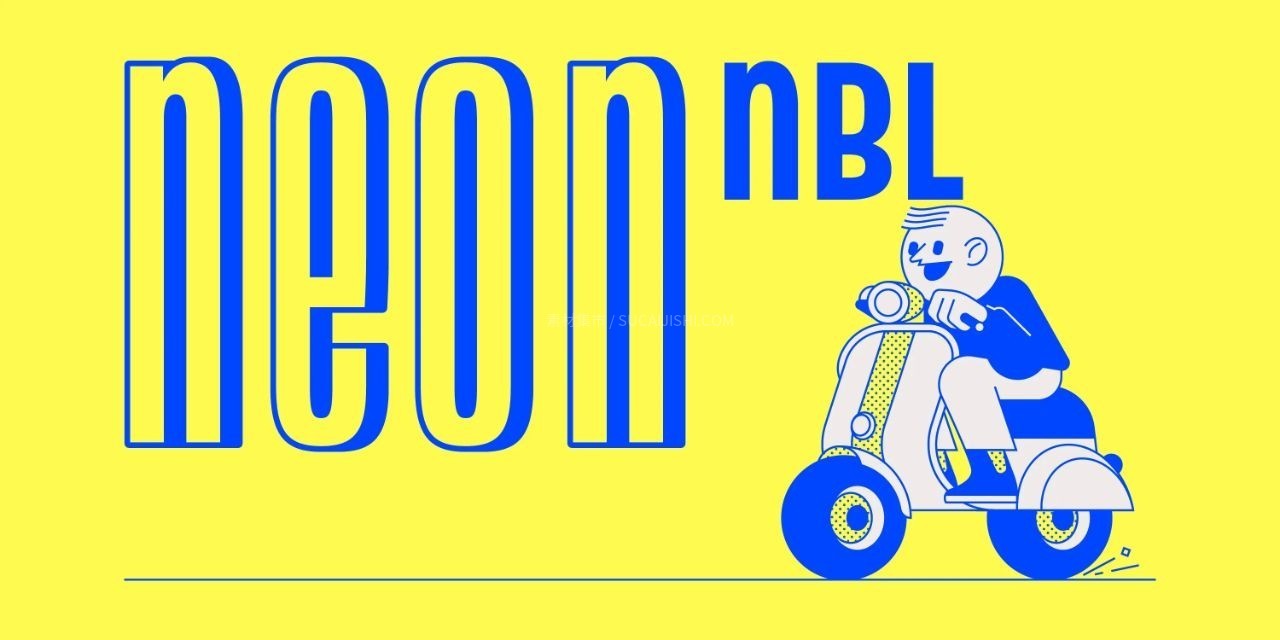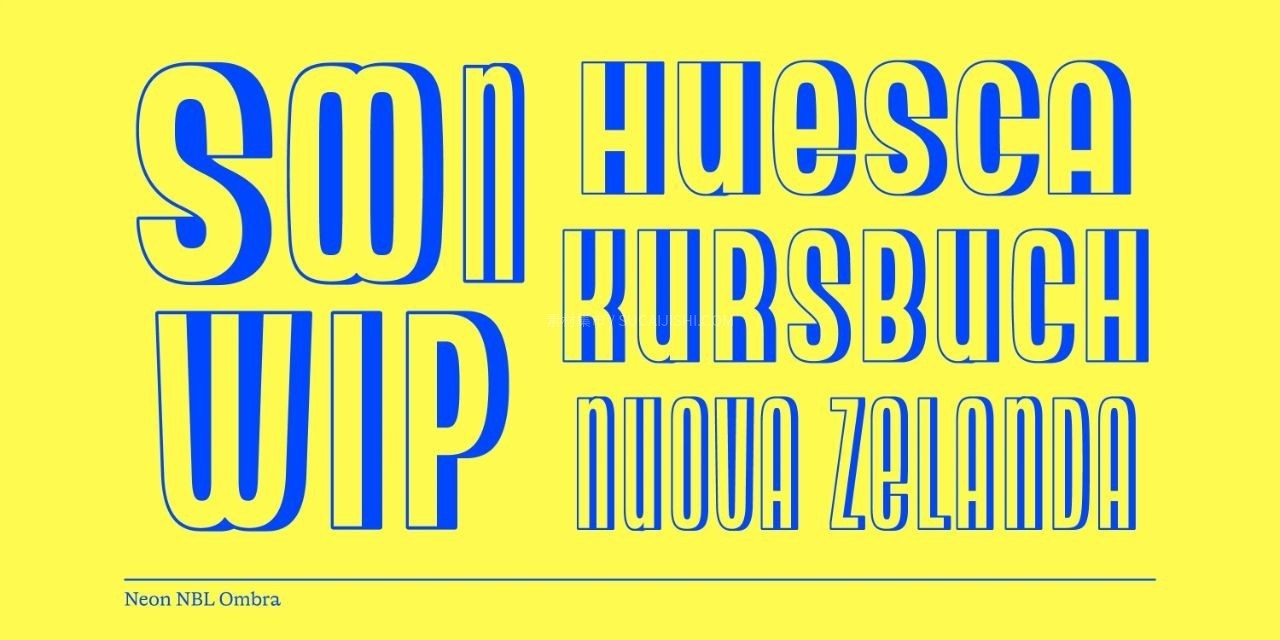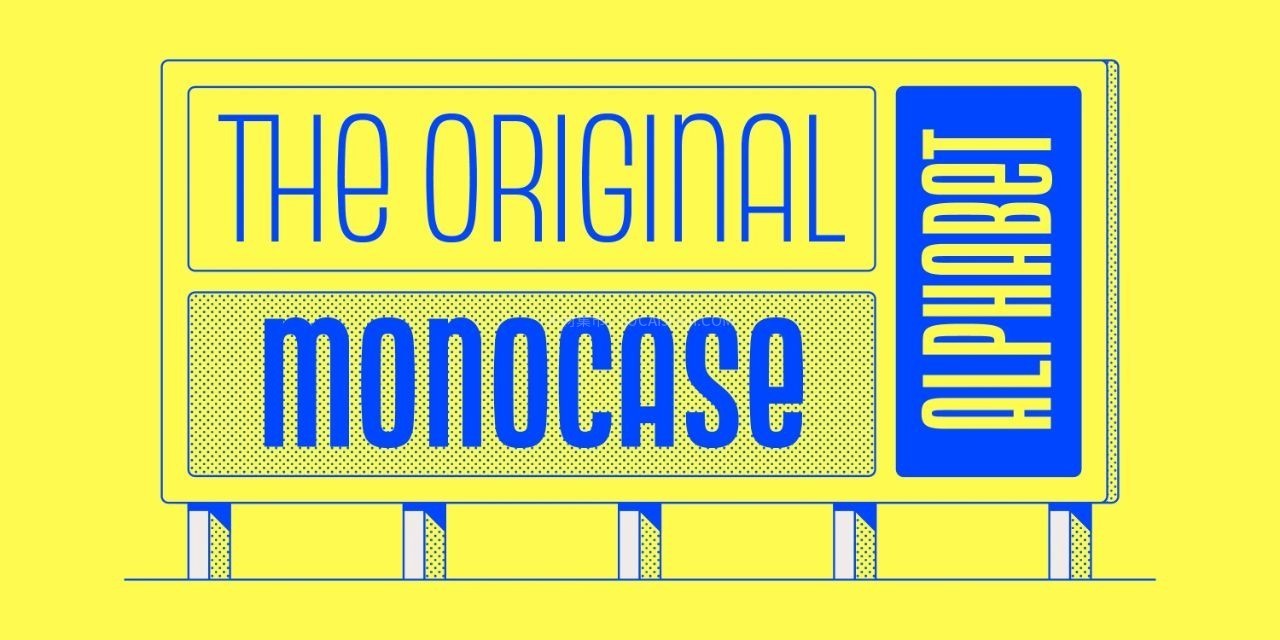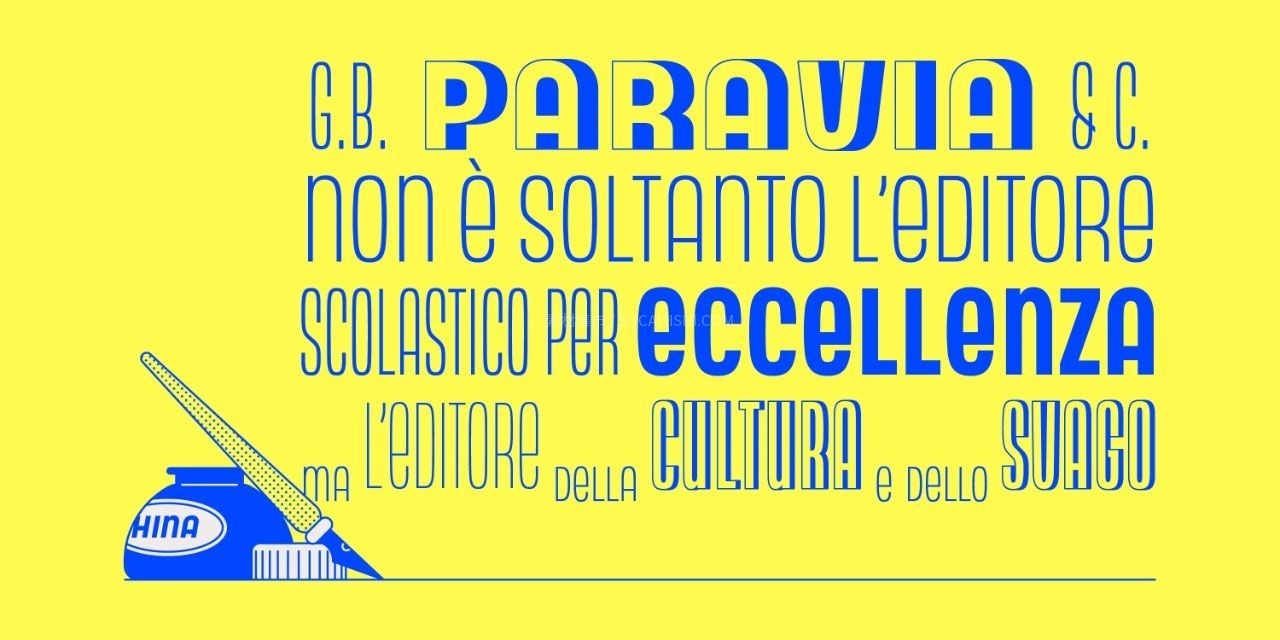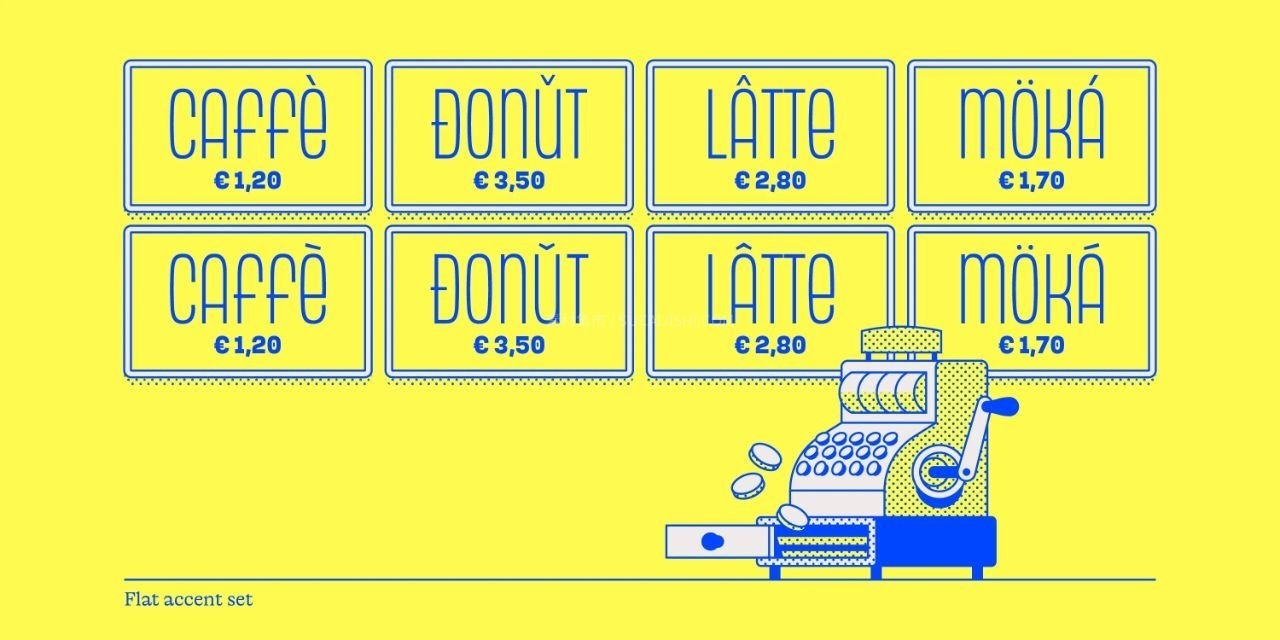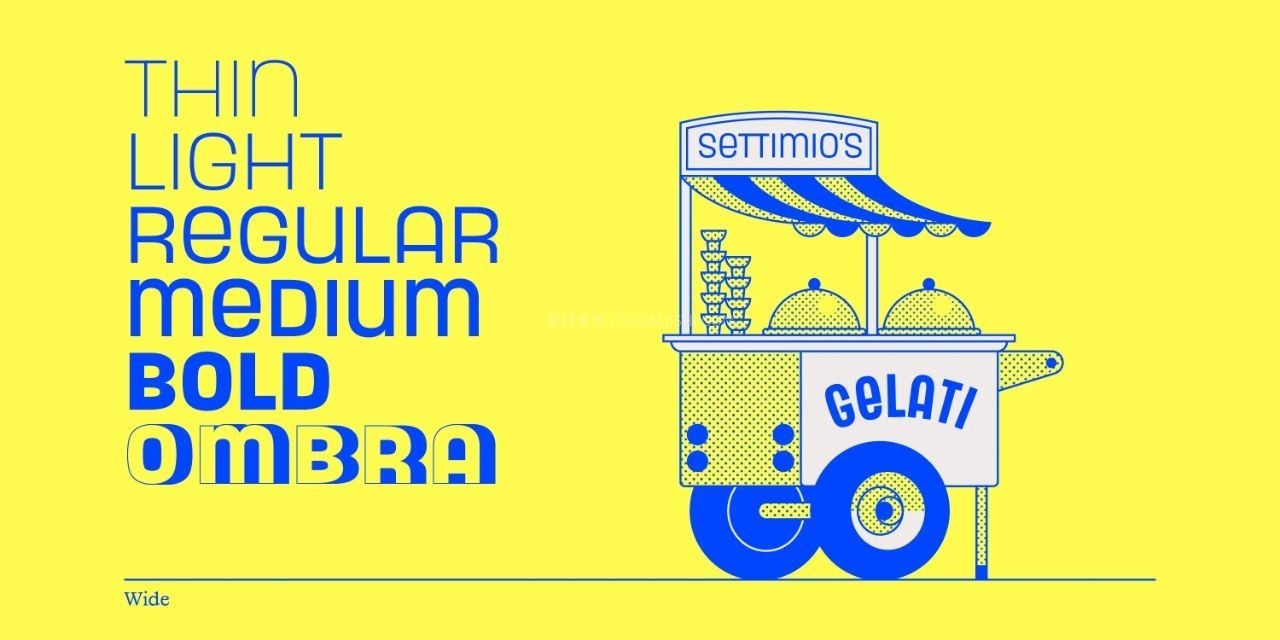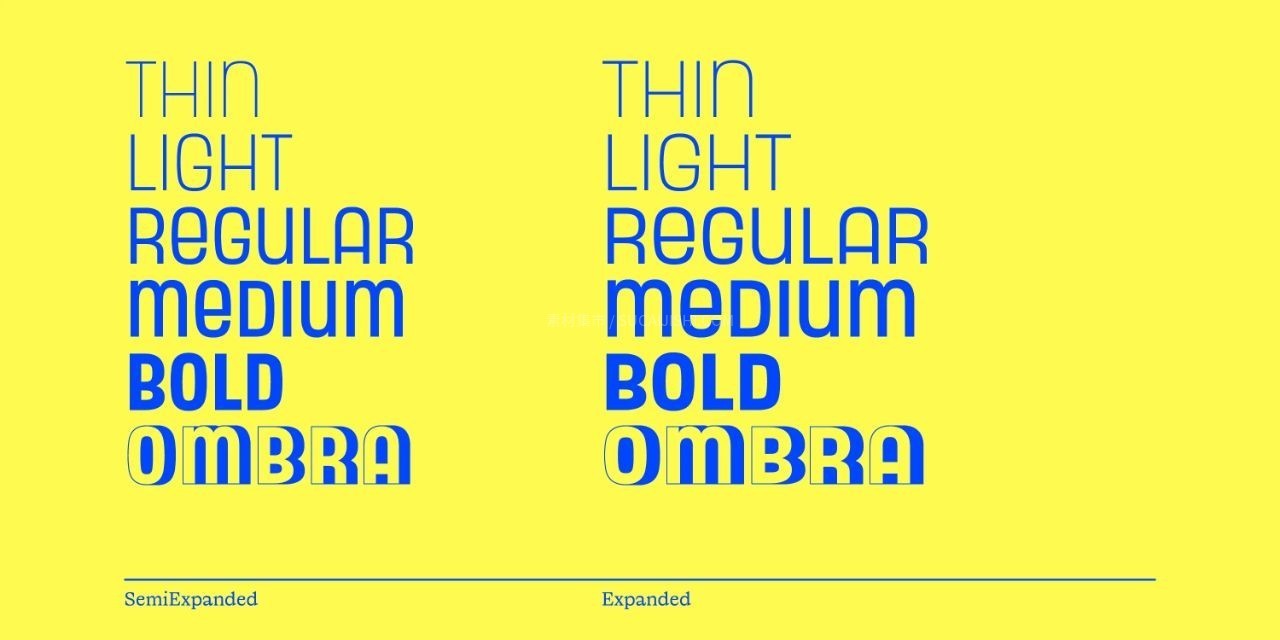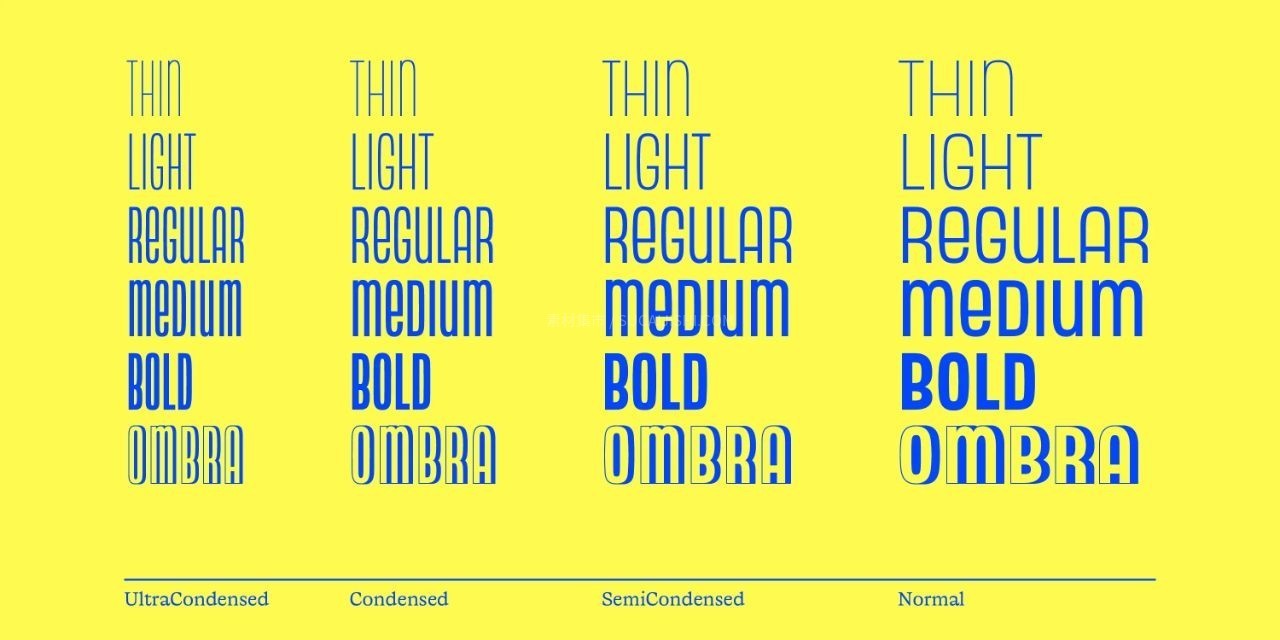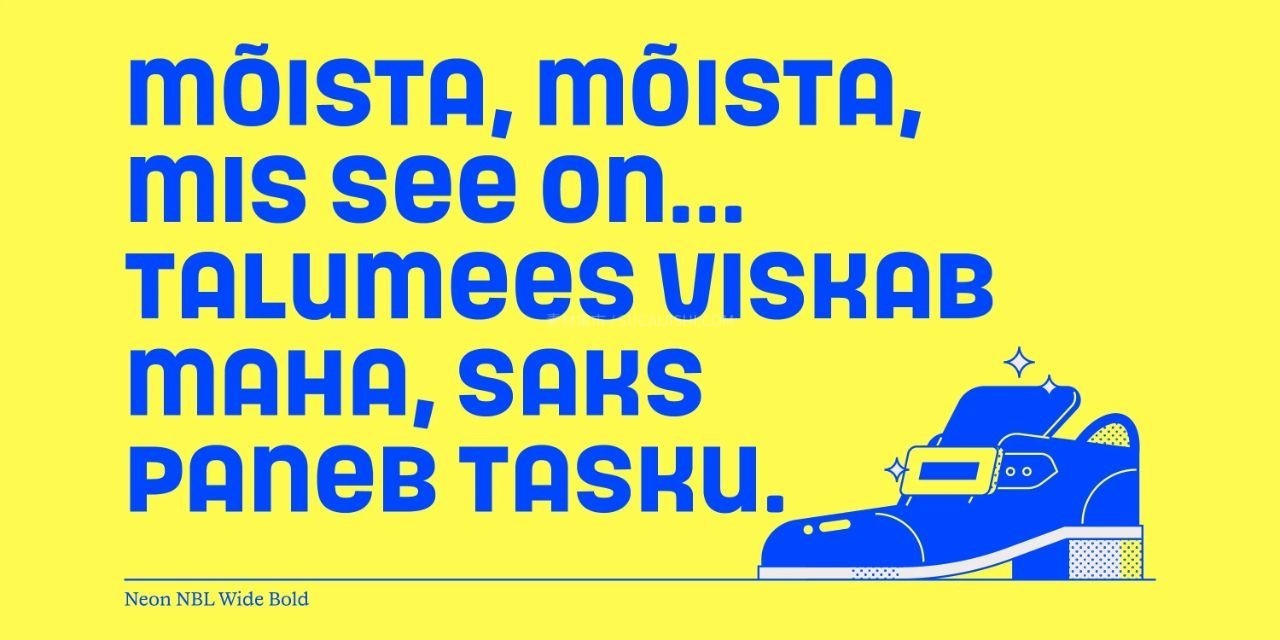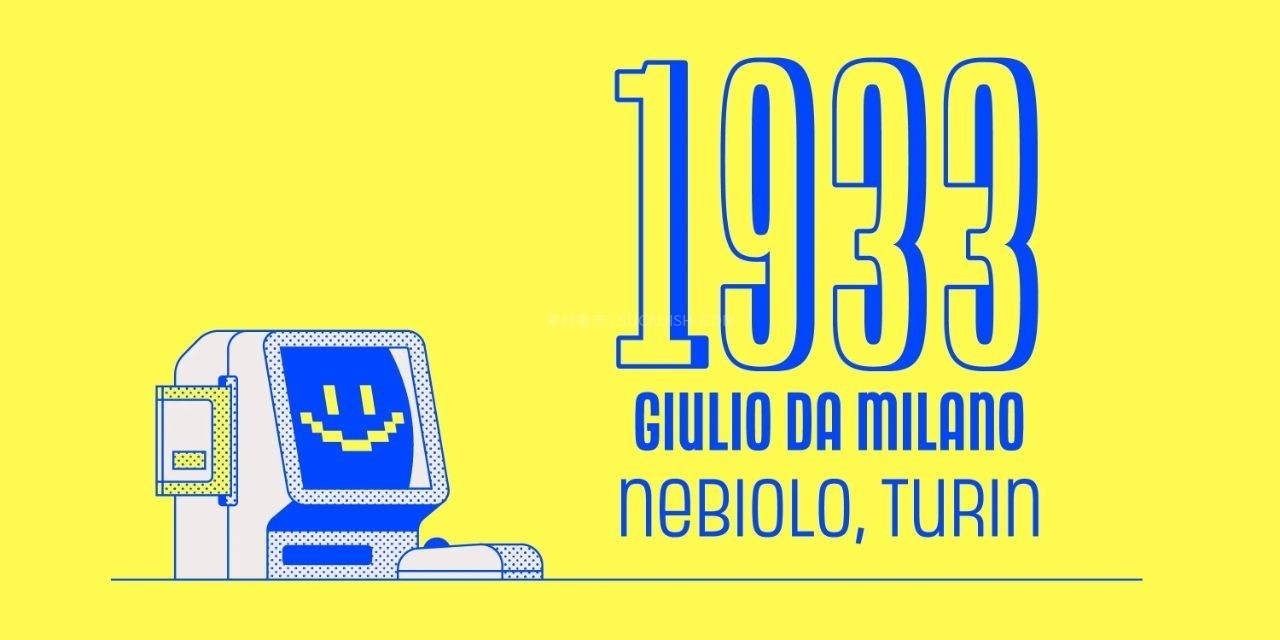
Neon NBL 复古几何字体家族
Neon NBL 是一款拥有42款丰富样式的超级字体家族,忠实数字化复刻了由 Giulio Da Milano 于 1930 年代设计的经典几何单字无衬线字体。这套字体系统不仅涵盖了从纤细到粗体、从超窄到宽广的完整字重与比例范围,还特别收录了带阴影的经典标题版本 Ombra。每款字体包含 700 多个字形,并经过精细的手工字距调整。其几何模块化的结构结合了微妙的光学细节处理,无论是大字号的视觉冲击还是小字号的易读性都能完美兼顾。字符集极其丰富,支持各类上下标点、分数、连字及所有欧洲语言的变音符号。